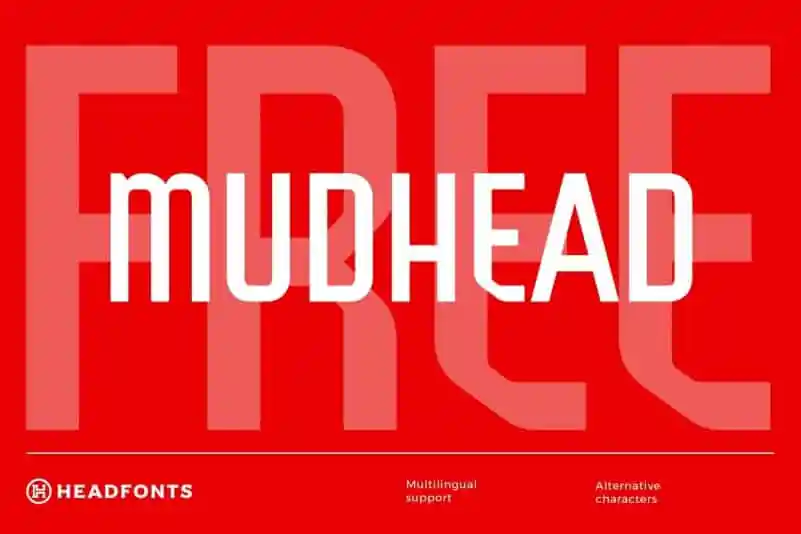
Mudhead Sans Serif Font – Download Grátis
A Mudhead Sans Serif é uma fonte moderna e dinâmica projetada para entregar um visual limpo e esportivamente agressivo aos seus designs digitais. Idealmente, ela se destaca como uma escolha ótima para aplicações que exigem um design alegre e vibrante, sem comprometer o legível. Fabricada pelo designer Headfonts, esta fonte é inspirada na cultura esportiva, combinando as cores agressivas dos uniformes modernos com linhas suaves e clean do tipo em abreviatura sans serif. Possui cinco pesos de negrito, umito a doisitos, serifs slab serif e versões em itálico para uma harmonia perfeita entre o visual despojado e a legibilidade. Suportando mais de 336 caracteres na cada fonte, a Mudhead é uma opção ideal para aplicações que exigem um visual competitivo e único, como logos esportivos ou posters de jogos importantes. Ela também oferece excelente leitura em qualquer formato digital, tornando-a uma escolha ótima para qualquer projeto que exige um olhar atraente e bem estruturado.